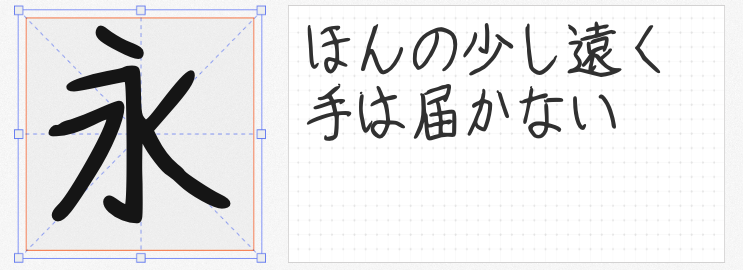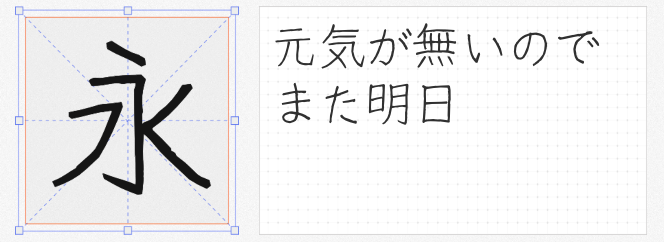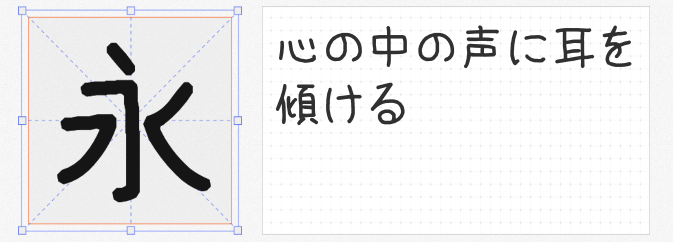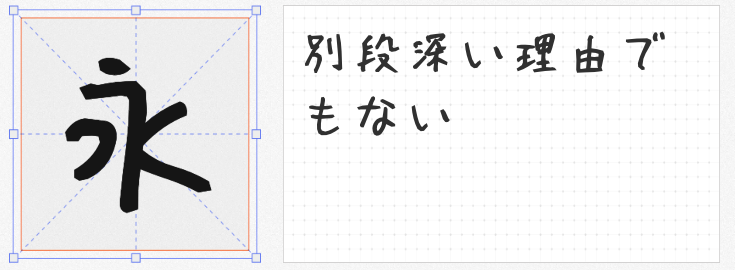
在日系风格设计中,手写字体是传递温度与个性的关键元素。本文精选四款免费商用日文手写字体,涵盖复古、纤细、童趣、灵动四大风格,助你轻松打造高辨识度作品。
由作者在笔记本上用钢笔书写后扫描数字化而成,槐树字体 Medium自带复古质感。其笔画粗细自然变化,保留纸张纹理与书写痕迹,适合用于怀旧主题海报、手账标题、书籍封面等场景。![]()
设计师手写的细鸣字体 B以纤细笔触见长,本字体提供3种字重(细/中/粗),适配从正文到标题的多层次需求。其字形方正规整,却因手写起伏保留灵动感,堪称PPT正文、产品包装、社交媒体配图的万能利器。![]()
合宜之诗 Bold以16000字符的庞大字符集脱颖而出,涵盖平假名、片假名、JIS汉字及英文字母,甚至包含游戏、动画常用符号。其笔画粗细对比强烈,每个字符大小与精细度微调,呈现出“非标准化”的手写趣味,尤其适合游戏标题、插画配文、儿童读物等场景。![]()
ほにゃ字 ver.Re以“每一笔都有生命”为设计理念,笔画弯曲如波浪,转折处自带弹性,仿佛文字在纸上跳跃。其风格童趣十足,适合儿童品牌LOGO、卡通表情包、节日贺卡等场景。